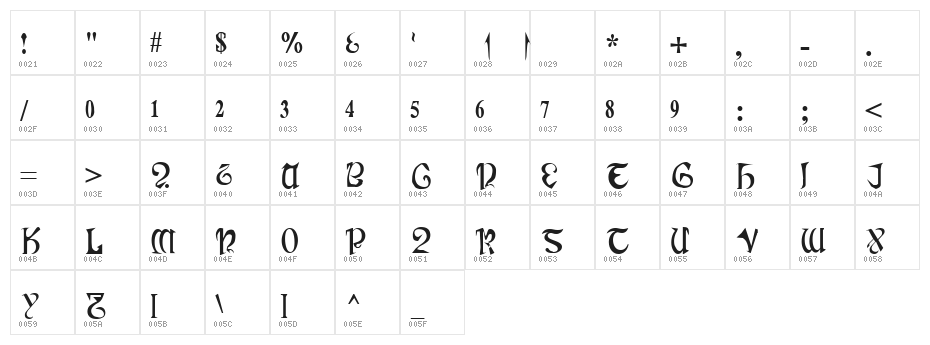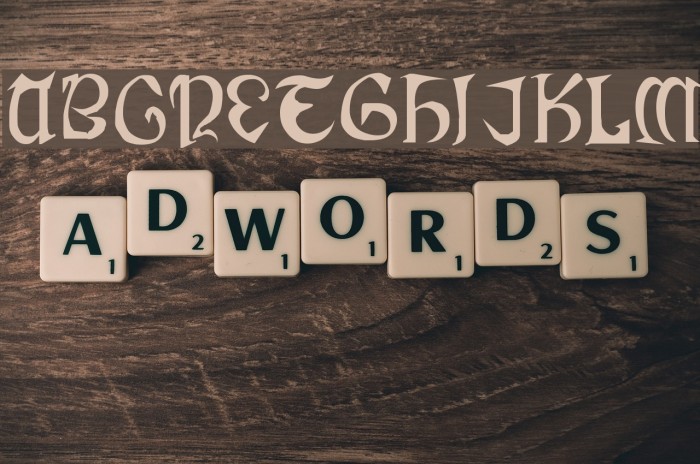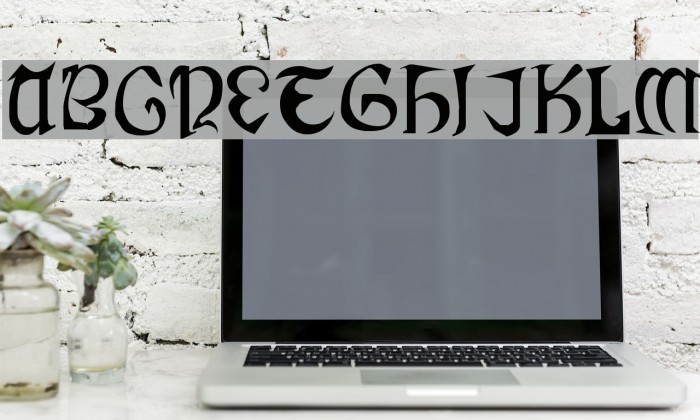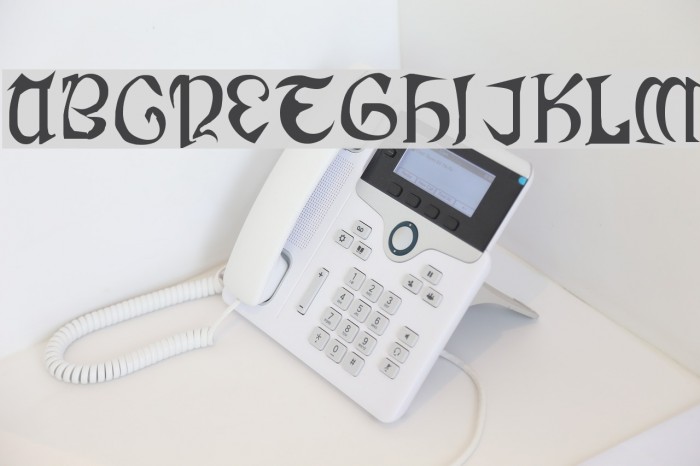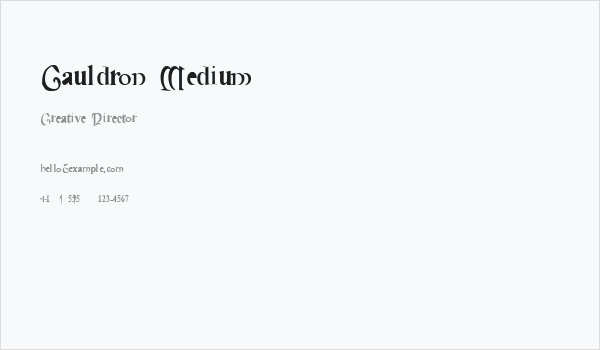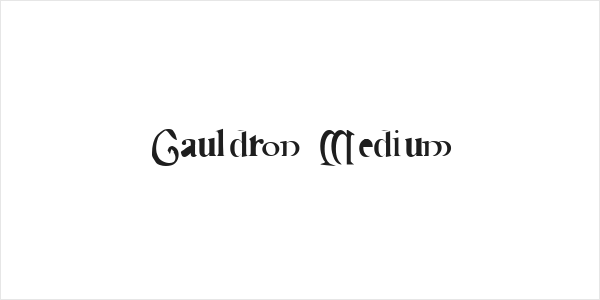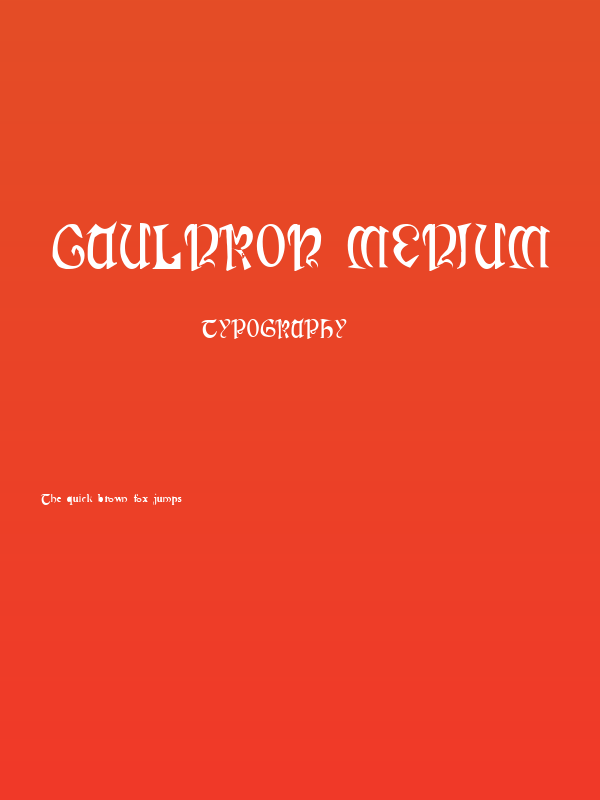
Cauldron Medium Font
✎ Gothic
| おすすめプロジェクト | Perfect for fantasy book covers, game titles, themed event posters, and any project needing a dramatic, medieval touch. |